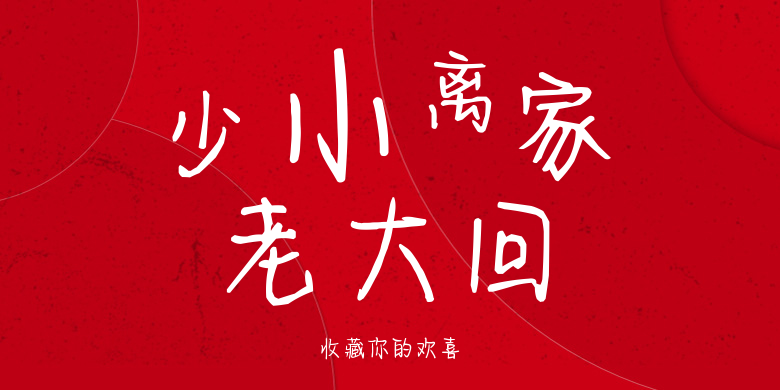
收藏你的欢喜
收藏你的欢喜,这款字体结构工整、笔画清晰,兼顾美观与易读性,适用于标题、正文、海报、包装、LOGO 等多种场景。字形优雅稳定,风格百搭耐看,适配日常排版与创意设计,让文字呈现更舒适、更具质感。收藏你的欢喜一笔一画,皆是细节,以均衡的比例、流畅的线条打造舒适视觉体验,字形端正大气,风格简约现代。无论是商业设计、品牌宣传还是日常排版,都能轻松驾驭,让文字更有格调与力量。收藏你的欢喜字体下载。